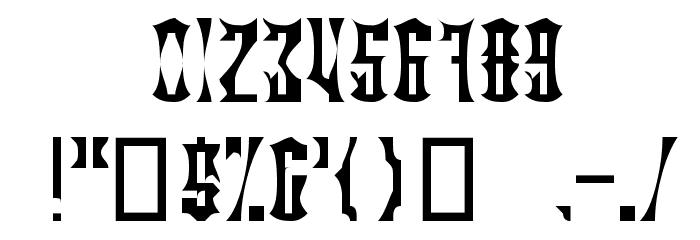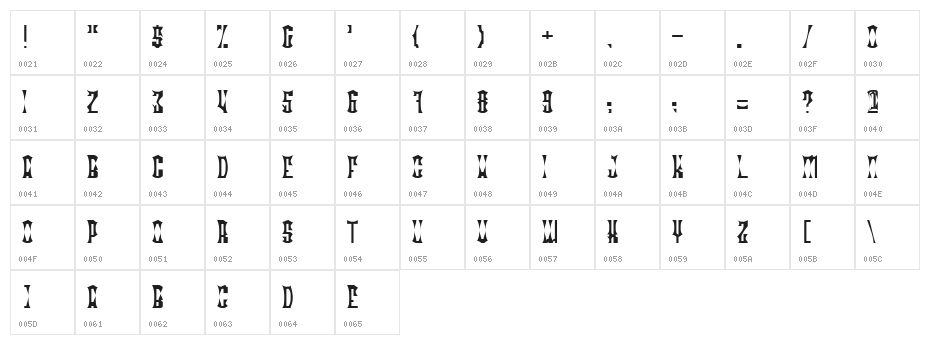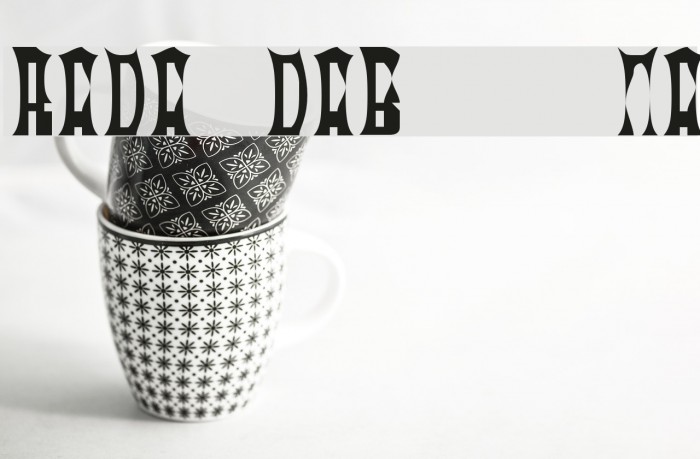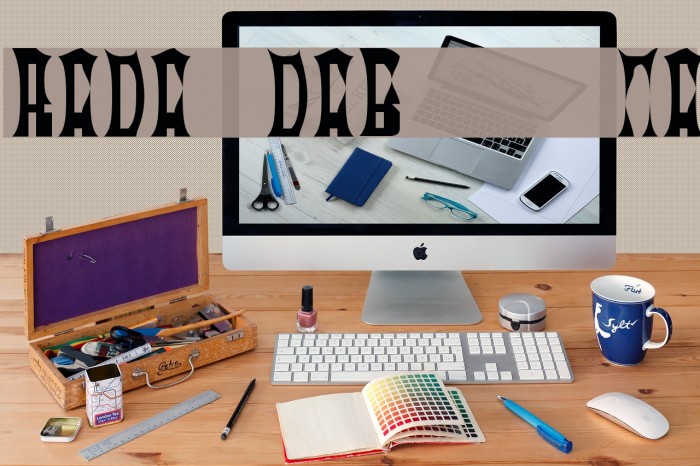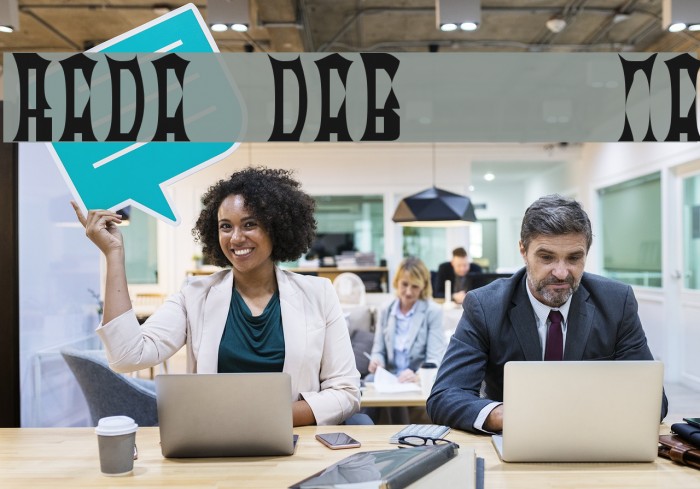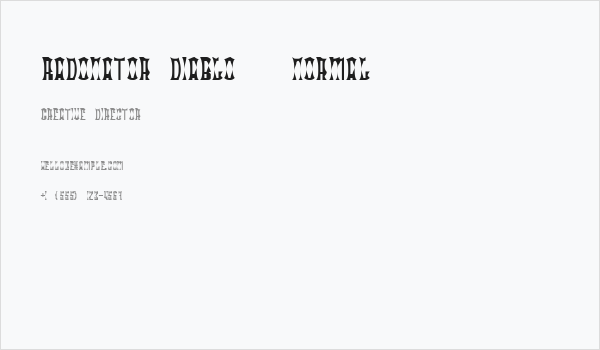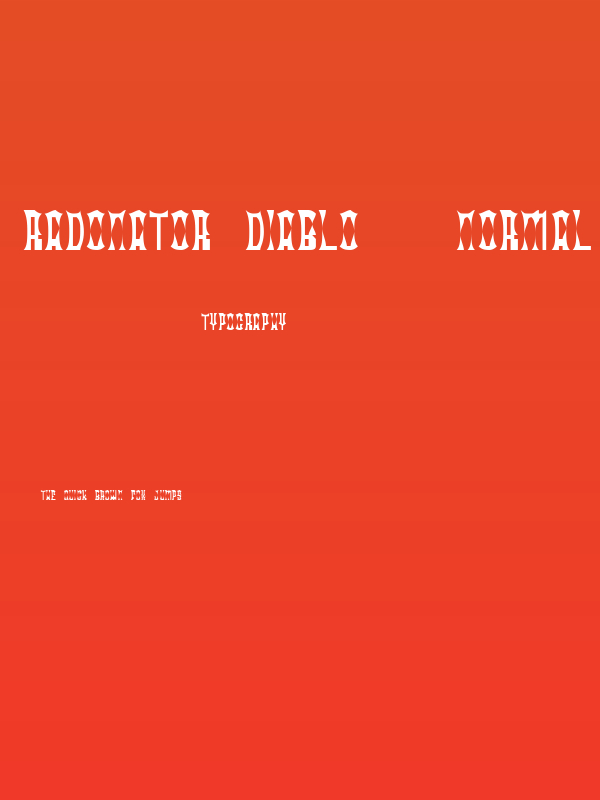
Radonator Diablo Normal Font
| Estilo geral | Gothic, Dramatic |
| Projetos propostos | Ideal for use in video game titles, movie posters, or any project requiring a dramatic and eye-catching typeface. |